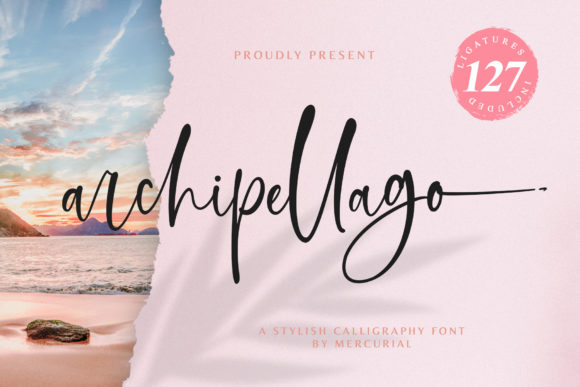
Fonte Archipellago para Cricut, Silhouette e designs para impressão.
Aprimore seus projetos com a fonte Archipellago , uma tipografia manuscrita moderna que lembra uma assinatura. Seu visual elegante e pessoal a torna perfeita para convites, logotipos e identidade visual.